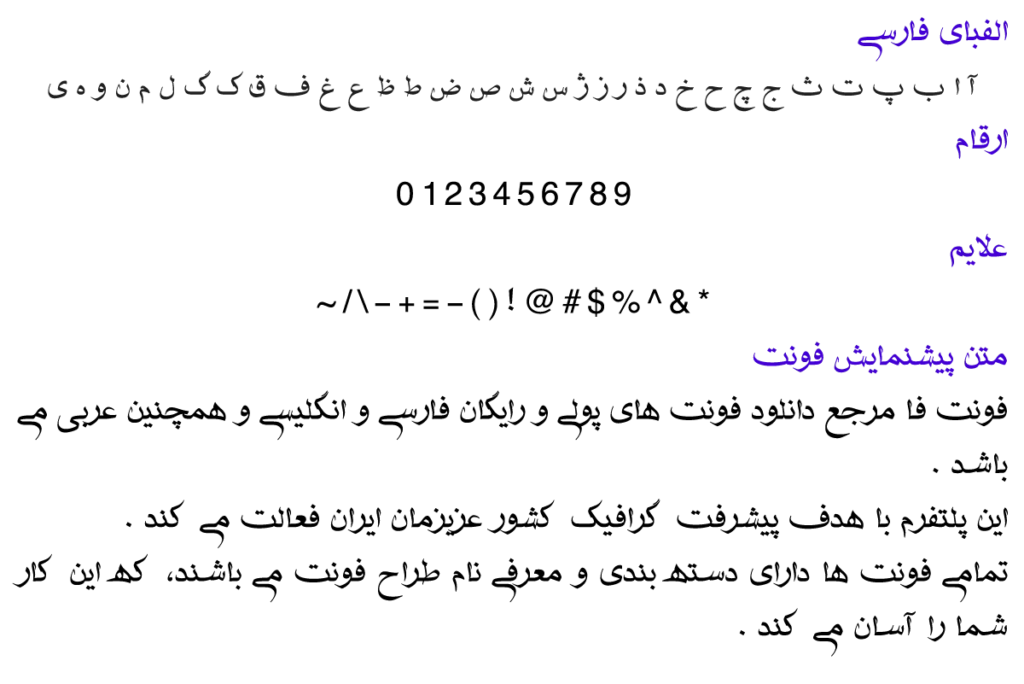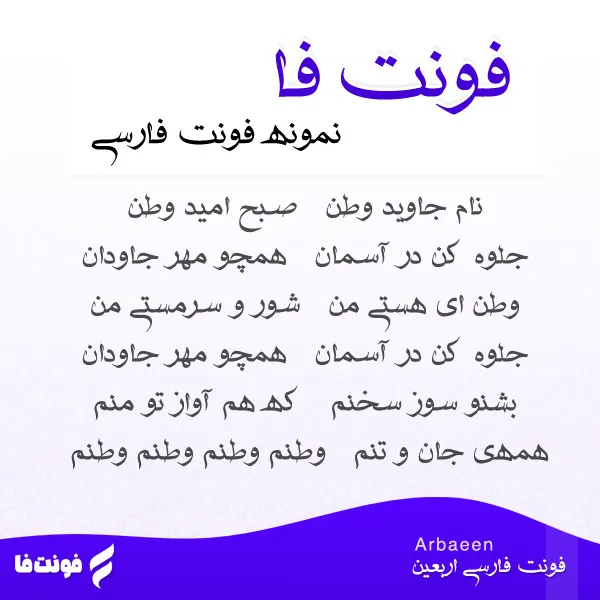
فونت فارسی اربعین – Arbaeen
سال ساخت فونت: 1393
طراح فونت: علی سواری نوع فونت: فونت فانتزی
پیشنمایش فونت اربعین
توضیحات و معرفی فونت اربعین
فونت فارسی اربعین ( Arbaeen ) از مجموعه فونت های آزاد می باشد، و نیز نوع فونت فانتزی می باشد.
فونت خوشگل مربوط توسط علی سواری در سال 1393 براساس نسخه ایرماگ فونت شفیق طراحی و ساخته شده است.
و نیز فونت Arbaeen در یک وزن معمولی است.
پیشنمایش این تایپ فیس زیبای فانتزی را در تصویر زیر میتوانید ببینید.